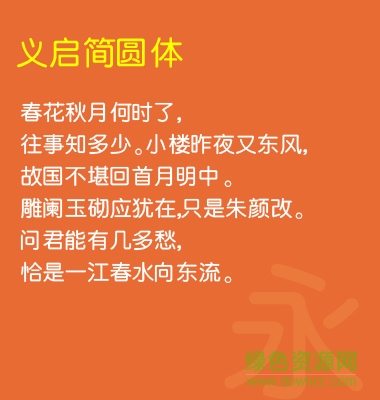
義啟簡圓體字體ttf版是一款端正好看的義啟字體,該字體方圓結(jié)合,字形清秀俊逸,廣告、海報(bào)等領(lǐng)域都有用到,需要的朋友歡迎在綠色資源網(wǎng)下載!
義啟簡圓體拐角處、筆畫末端為圓弧狀。字體清晰、端正、嚴(yán)肅,適合于報(bào)紙大字頭、圖書封面、招牌、廣告、網(wǎng)站標(biāo)題的制作。簡圓體,即簡約而不簡單。義啟簡圓體,讓右邊的拐彎處更圓,更加接近于圓形。